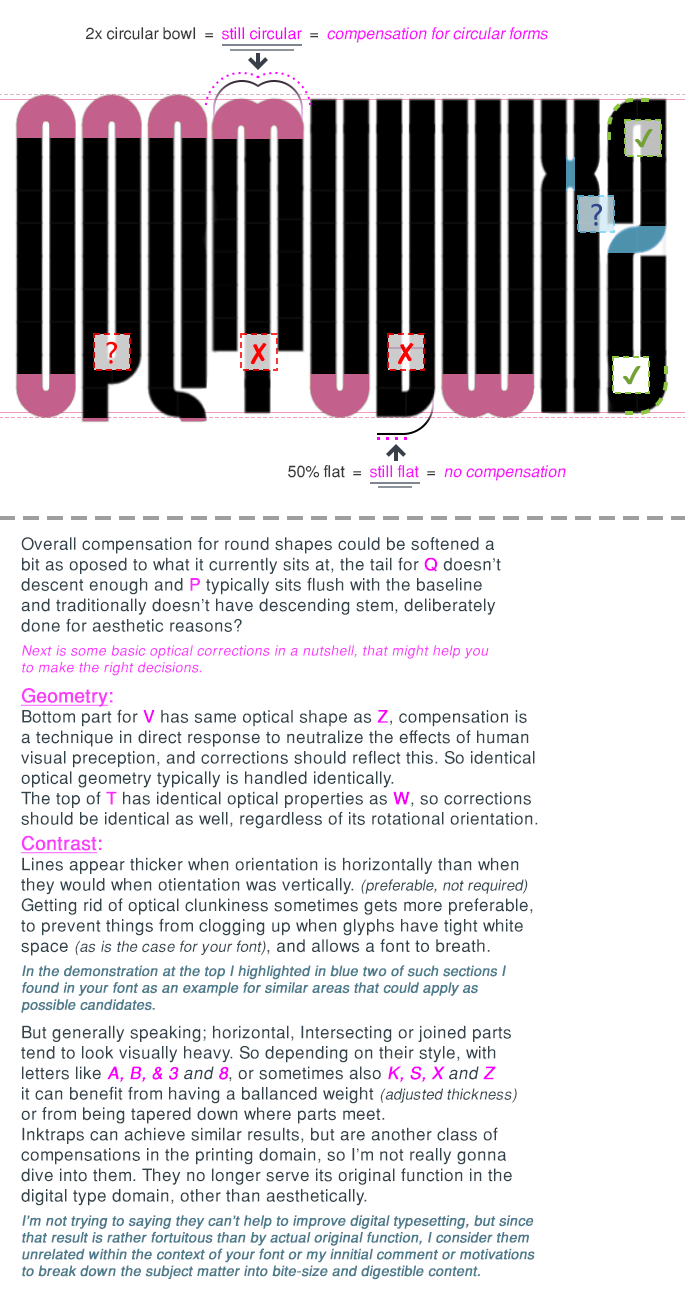
Интересный шрифт, очень хорошо, что в нем есть оптические компенсации. Мне кажется, к нему хорошо бы сделать в пару шрифт с более привычными формами, без округлений, чтобы эти шрифты между собой сочетались (я бы сам его сделал, открой ты возможность клонирования). Даже придираться ни к чему не хочется, это 10/10.
Nice, but I wonder if you could pick another name for this font? https://fontstruct.com/fontstructions/show/1413593/at-zabor
I'm with the people: great font here. Perhaps the optical compensation is a little bit too obvious, IMHO.
Здравствуй, Евгений, надеюсь, ты не против коммента на русском языке, я не знаю, говоришь ли ты на нём или, может, ты с Украины, судя по фамилии. Короче, хотел сказать, что ты забыл добавить оптическую компенсацию в заглавную Г сверху и украинскую Є снизу. И еще стоит привести в божеский вид буквы Д Щ Ц, в том числе строчные, чтобы не было такого большого полуапроша справа.
Nice work so far and great looking style, I do have some areas I'd like to point out and get into a bit further, following elmoyeniques opinion but with some additional technical knowledge on some of the issues.